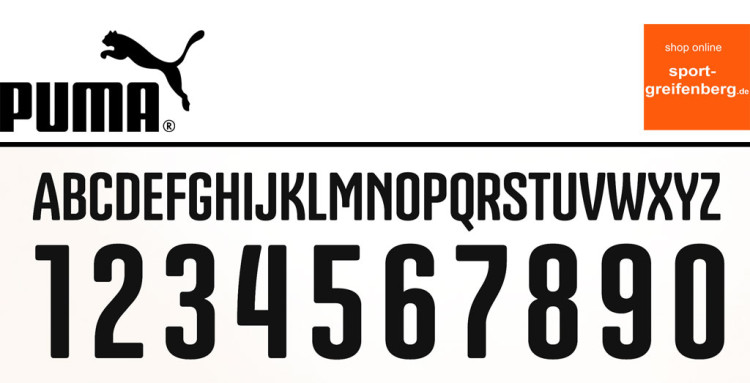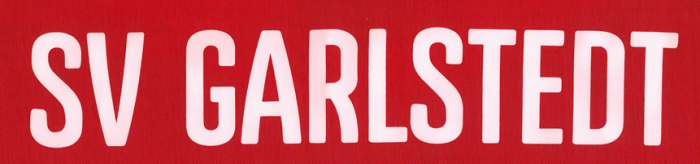
Vereinsschrift gesucht
leider haben alle Online-Tools versagt. Dabei finde ich das leicht gebogene "V" und auch das "A" ziemlich einmalig (und hübsch! :-))
Aber wie gesagt... Ich bin jetzt schon 2 Stunden damit beschäftigt und komm nicht weiter.
Hat jemand eine Idee?
PS: Im Anhang ist der Scan von einem Trikot
Bei Trikots werden gern Plotter-eigene Schriften (die keine Satzschriften sind) verwendet, ich würde daher auch mal den Trikotlieferanten fragen.
Ja, das ist schon passiert.
Das Trikot kam so nicht vom Hersteller sondern der Schriftzug wurde nachträglich aufgebracht.
Von wem ist leider unbekannt. Wahrscheinlich von einem CopyShop.
Ich finde auch das die verdammt nach DIN ausssieht. Gerade das G.
Aber der "freundliche Schwung". Der fehlt leider auch bei den rounded Varianten.
Also bei den Grotesque Schriften hatte ich schon geschaut, aber bei den ganzen Schnitten... Die Geogrotesque passt super!
Aber auch die Essential Pragmata ist klasse... Danke!
Essential Pragmata: Ich bin einfach auf www.myfonts.de gegangen und habe »condensed« als Suchbegriff eingegeben. Dann bin ich die angezeigten Suchergebnisse durchgegangen, bis ich etwas Passendes gefunden habe. Das hat vielleicht so fünf bis zehn Minuten gedauert. :-)
Freu dich aber nicht zu früh, denn diese Schrift wirst du nicht für eine allgemeine Verwendung bekommen.
Diese Trikot-Schriften sind exklusiv für die Trikothersteller entworfen, und bei denen markenrechtlich geschützt und werden dann auch ausschließlich für die Beflockung von Trikots des Herstellers selbst lizensiert.
Im Grunde sollte man sich bei Trikotschriften merken: Statt in üblichen Schriften-Sammlungen zu forschen, sollte man zuerst fragen;: Wer ist der Hersteller der Sportkleidung? Und dann noch: In welcher Saison wurden die Trikots beschafft.
Ja, ja... zu früh gefreut. Hab das mit Eduardo Manso auch schon gelesen, nachdem ich die Schrift als TTF aber sehr schnell gefunden hatte. Klar, das war nicht legal.
Zumindest darf man dann die Geogrotesque auch auf Trikots beliebiger Hersteller aufplätten, ohne das das 2. Herzogenauracher Sportartikel-Unternehmen daraus eine Markenfälschung konstruieren kann, was eventuell erheblich teurer würde, als die Tikots gleich da zu bestellen.